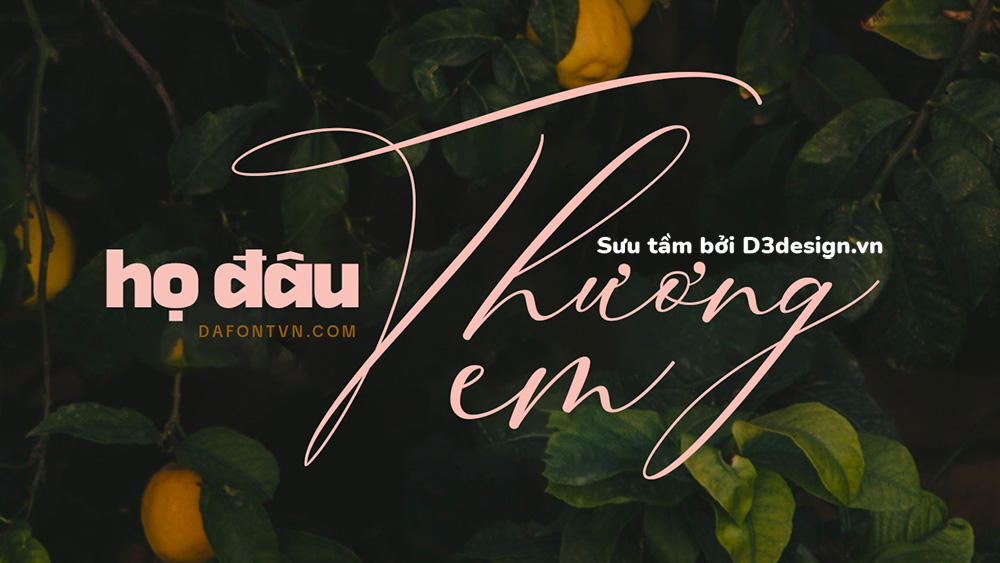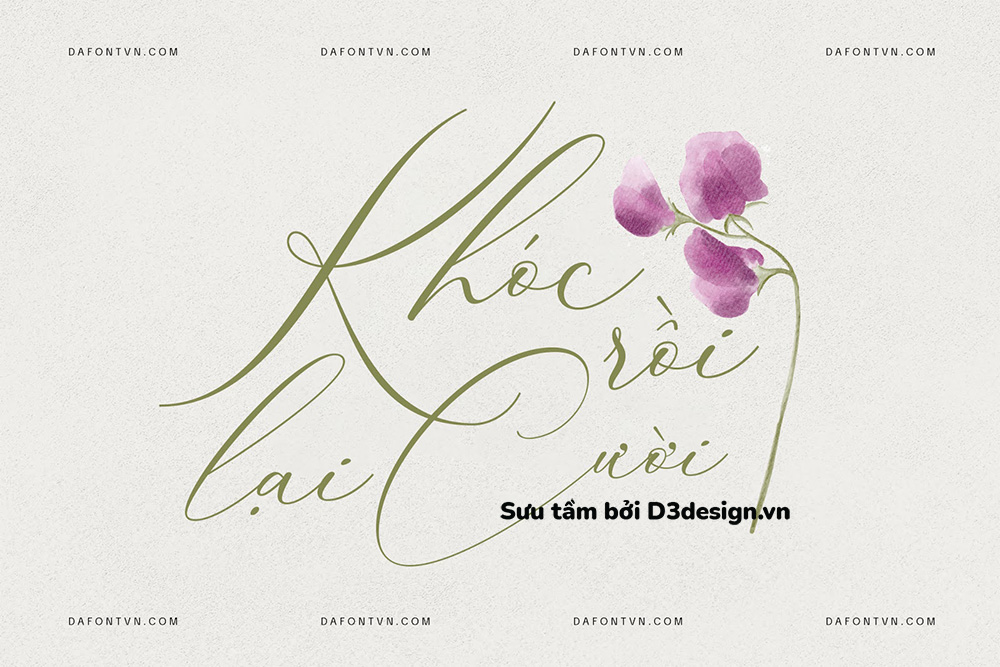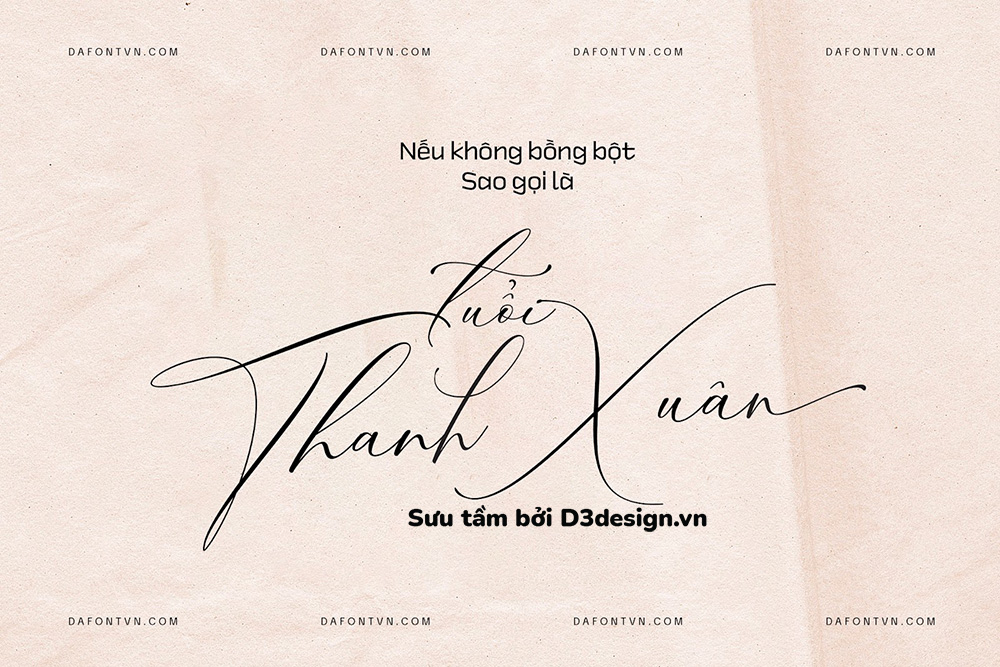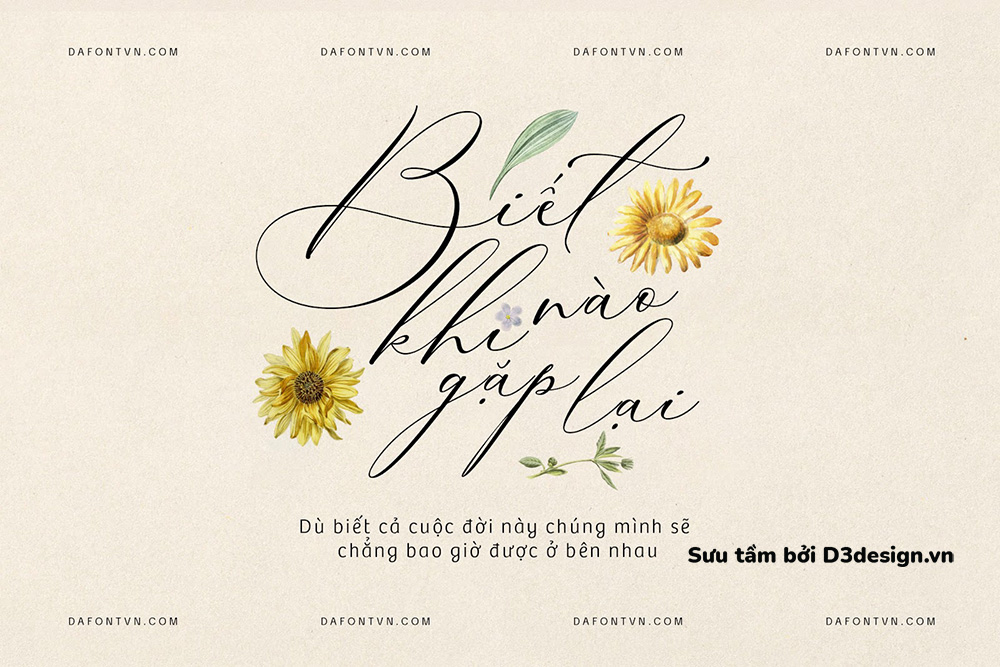
Font Việt Hóa - Boheme Floral Mang Phong Cách Cổ Điển Viết Tay
Boheme Floral Font - là một kiểu chữ calligraphy cổ điển với các đường nét thiết kế ấn tượng giữa các chữ cái để bạn có thể tạo ra những tác phẩm đẹp mắt.
Một trong những yếu tố chính tạo nên sự khác biệt của phông chữ Boheme Floral là thiết kế vẽ tay của nó, được tạo ra để mô phỏng hoàn hảo kiểu chữ viết tay tự nhiên. Điều này đạt được nhờ sự kết hợp của hơn 50 chữ ghép, dùng để tạo ra sự chân thực và tự nhiên hơn.
Boheme Floral là một trong những kiểu chữ hoàn hảo mà bạn có thể sử dụng để thiết kế danh thiếp, thư mời, thiệp chúc mừng, bìa sách, thiệp mời đám cưới, quote... hoặc bất kỳ thiết kế nào.
Font chữ này ra đời từ năm 2018 vì vậy khá nhiều ký tự và dấu rất lộn xộn chưa được tối ưu. dafont.vn đã chỉnh sửa, kerning và đã tối ưu lại font. (Đây là font việt hóa theo yêu cầu)